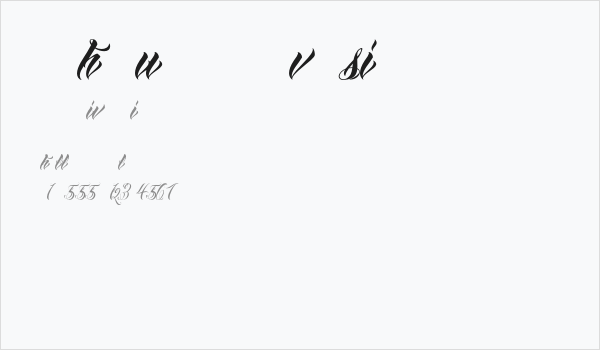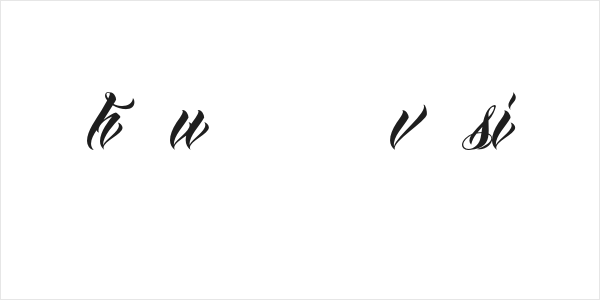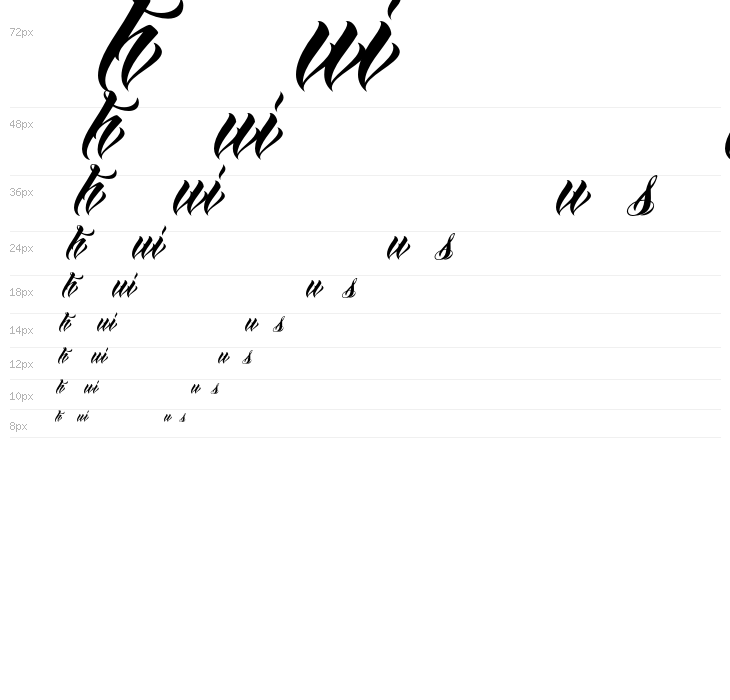
AnhaQueendemoversion Font
| Caso d'uso | Logos, Invitations, Branding |
| Progetti proposti | Ideal for wedding invitations, luxury branding, high-end product packaging, and elegant event signage. |